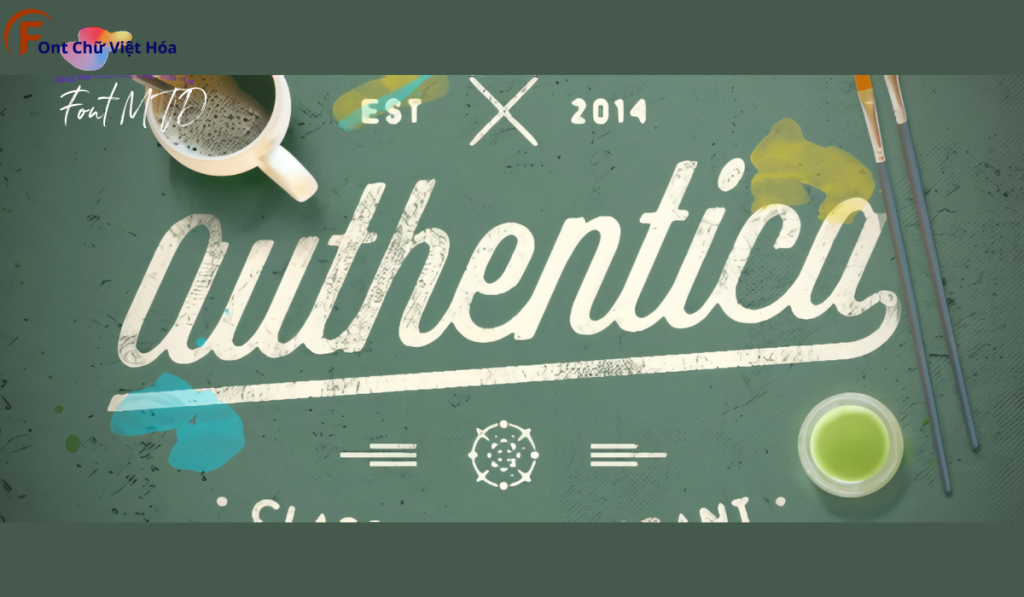
Font MTD Authentica Rough Việt Hóa
Kiểu chữ: Có chân
Độ dày: Regular, Bold, Light, Medium
Font MTD Authentica Rough Việt Hóa, thuộc bộ font MTD, mang phong cách mạnh mẽ và cá tính, phù hợp cho các dự án thiết kế như poster, logo, và bao bì sản phẩm. Với các nét chữ có chân và độ dày đa dạng, Font MTD Authentica Rough Việt Hóa không chỉ dễ đọc mà còn tạo cảm giác sáng tạo và độc đáo. Việc Việt hóa font giúp người dùng dễ dàng tích hợp vào các thiết kế tiếng Việt, mang lại sự tiện lợi và nâng cao tính thẩm mỹ.